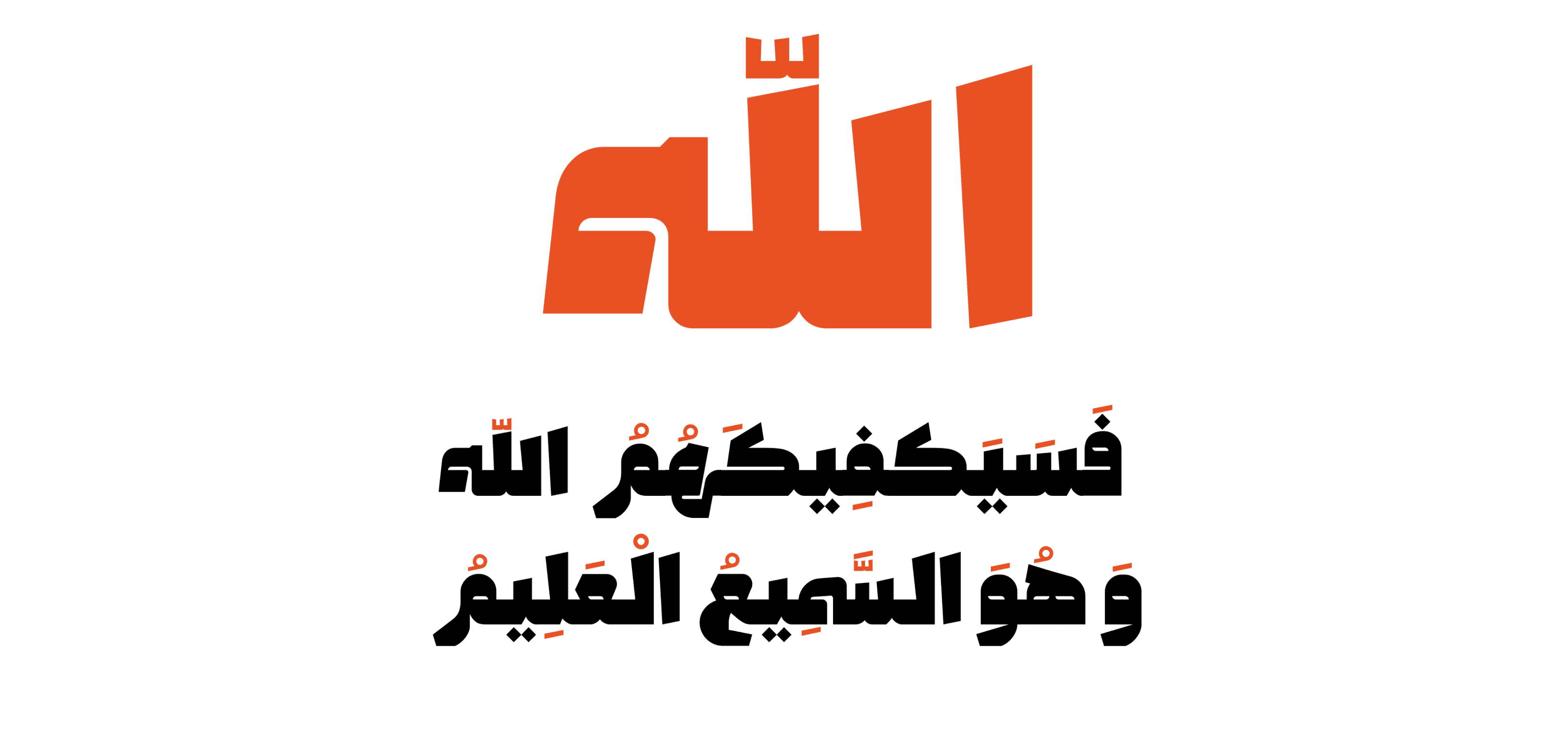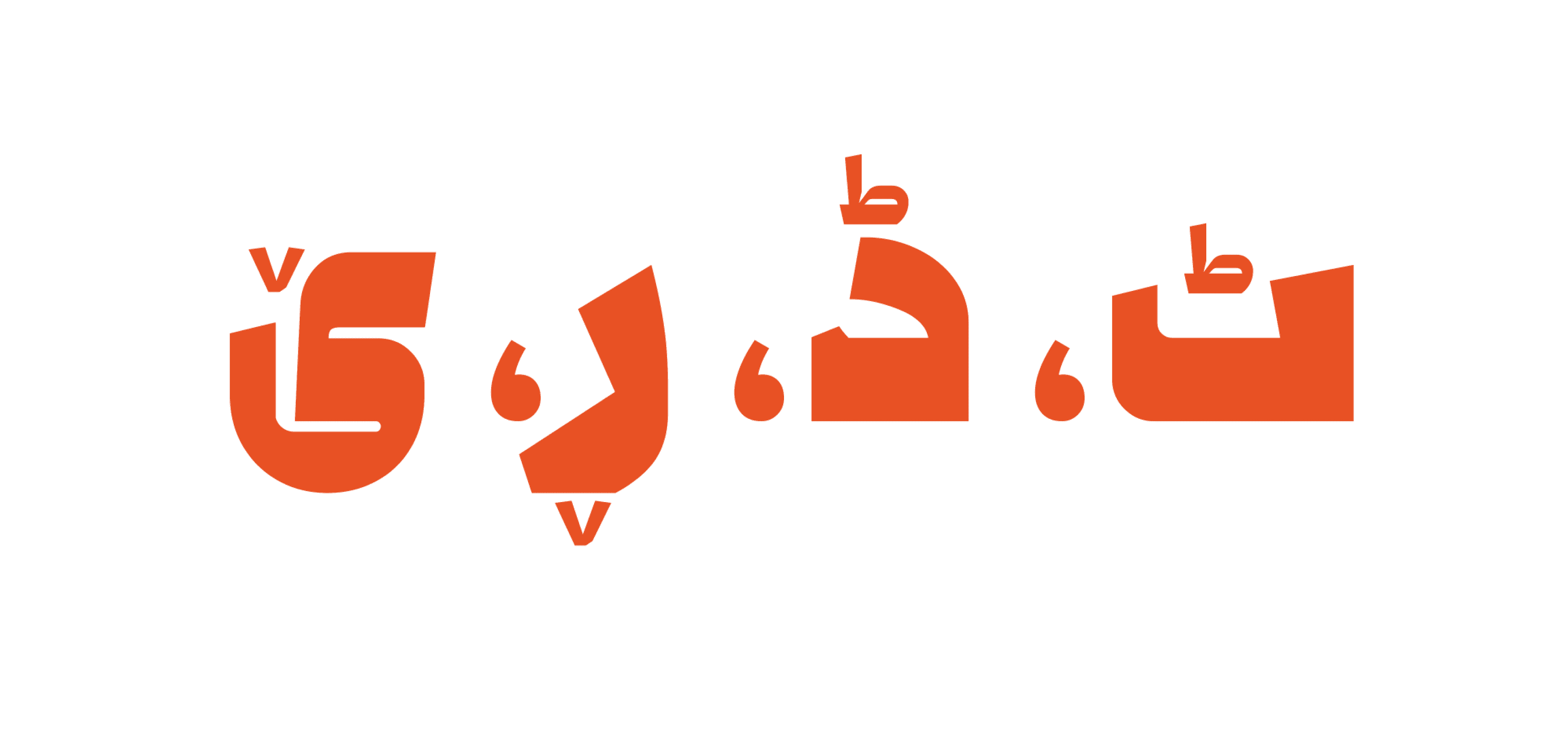
فونت وزين سافت يتميز بزواياه المستديرة وحوافه الأقل حدّة، كما أن حروفه أكثر سماكة من الخطوط العادية. يُستخدم هذا الخط لتسليط الضوء على كلمة معيّنة في الإعلانات أو كعنوان لموضوع ما. وزين سافت بخطوطه الدائرية مناسب للعناوين، والعناوين الفرعية، وسائر النصوص التي يجب أن تبرز للنظر.